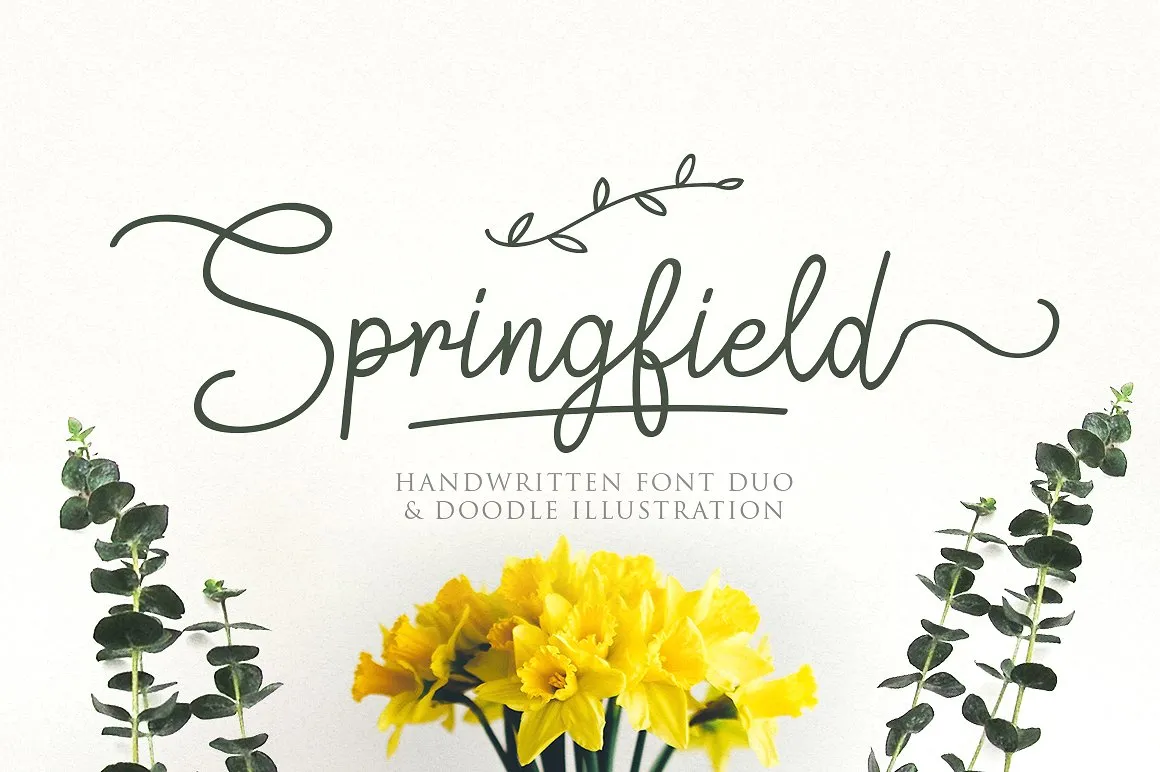
Descubra Springfield Script Font, uma nova opção premium para designers que buscam criatividade e elegância. Lançada por 178-MC, esta fonte vem equipada com um conjunto divertido de ilustrações desenho que permitem criar tipografia única em poucos cliques. Com dois diferentes conjuntos de fontes e uma ilustração colorida, você pode personalizar seu trabalho de maneira rápida e original. Springfield é ideal para projetos de marca, logotipos, convites ou embalagens de produto, mas também se adapta bem como overlay texturizado sobre qualquer imagem de fundo. Suavemente fluida enquanto digita, ela parece uma assinatura perfeita. Seja para adicionar um toque único a sua designação, criar cartazes publicitários ou decorar qualquer página web, Springfield é uma excelente escolha. Essa fonte é perfeitamente adaptável a muitos ambientes e propósitos, tornando-a um investimento valioso para seu portfólio de recursos gráficos. Se você está procurando por uma fonte que brinque com a tipografia em um nível único, então Springfield Script Font é definitivamente algo para adicionar à sua seleção.